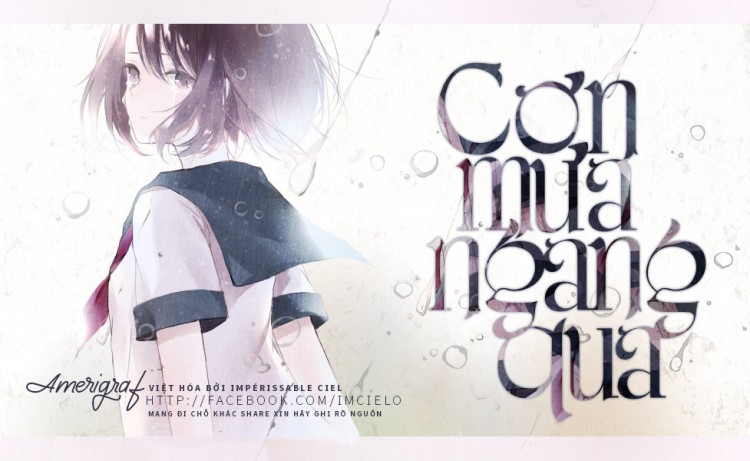
Tải Ngay Font việt hóa iCiel Amerigraf – Nét Vẽ Phóng Khoáng Cho Thiết Kế Việt
Giới thiệu về Font việt hóa iCiel Amerigraf
Trong thế giới đồ họa hiện đại, việc tìm kiếm một bộ Font Chữ vừa mang nét nghệ thuật vừa đảm bảo tính ứng dụng cao là điều vô cùng quan trọng. Font việt hóa iCiel Amerigraf chính là giải pháp hoàn hảo cho những ai yêu thích phong cách brush (nét cọ) đầy cá tính. Đây là một bộ phông được thiết kế dựa trên cảm hứng từ những đường nét thủ công tự nhiên, mang lại cảm giác phóng khoáng, mạnh mẽ nhưng không kém phần uyển chuyển. Đặc biệt, với phiên bản đã được iCiel Việt hóa chỉn chu, người dùng có thể hoàn toàn yên tâm sử dụng tiếng Việt có dấu mà không lo bị lỗi hiển thị hay mất nét.
Ưu điểm nổi bật của Font việt hóa iCiel Amerigraf
Phong cách thiết kế độc đáo và linh hoạt
Font việt hóa iCiel Amerigraf sở hữu những nét vẽ đậm nhạt đan xen, tạo hiệu ứng thị giác như được viết bằng cọ thật trên bề mặt giấy. Điều này làm cho các thiết kế trở nên sống động và có chiều sâu hơn. Phông chữ này cực kỳ phù hợp cho các dự án thiết kế tiêu đề sách, bìa tạp chí, các ấn phẩm quảng cáo hay logo thương hiệu cần sự phá cách. Đối với các bạn học sinh và giáo viên, việc sử dụng bộ font này trong các bài thuyết trình hay thiết kế báo tường sẽ giúp nội dung trở nên thu hút và sáng tạo hơn rất nhiều.
Khả năng ứng dụng đa dạng trong thực tế
Không chỉ dừng lại ở các ấn phẩm in ấn, bộ font này còn hoạt động xuất sắc trên các nền tảng kỹ thuật số như banner website, hình ảnh mạng xã hội hay thiết kế áo thun. Sự kết hợp giữa nét hiện đại và phong cách đường phố giúp sản phẩm của bạn luôn nổi bật giữa đám đông.
Hướng dẫn sử dụng và kết luận
Để tận dụng tối đa vẻ đẹp của bộ font này, bạn nên kết hợp nó với các phông chữ không chân (sans-serif) đơn giản để tạo sự cân bằng. Việc tải về và cài đặt vô cùng dễ dàng, giúp bạn nhanh chóng biến ý tưởng thành hiện thực. Hãy truy cập ngay để sở hữu Font Miễn Phí, Font Việt Hóa, Font việt hóa iCiel Amerigraf và bắt đầu hành trình sáng tạo của mình ngay hôm nay.